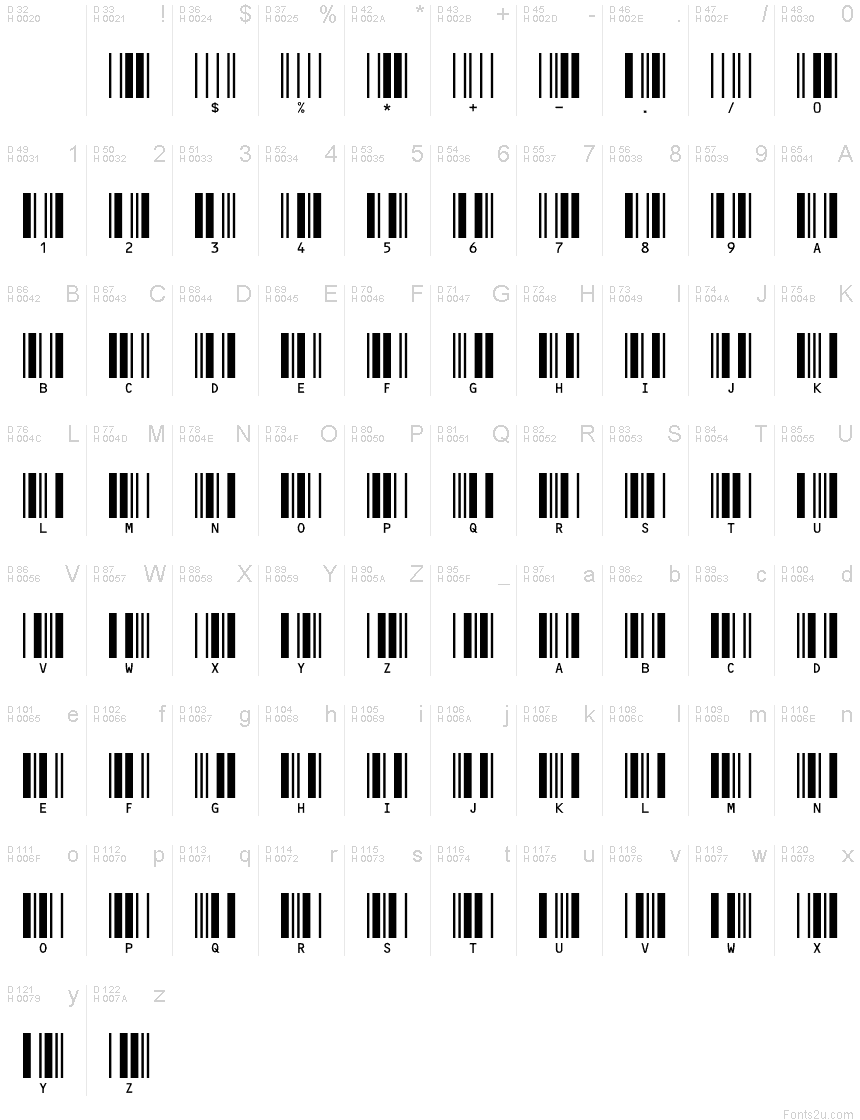
C39HrP24DlTt 字体
C39Hr 字体家族,包含 4 款字体
C39HrP24DlTt
由 Bear Rock Technologies Corp. 开发的 C39HrP24DlTt 是一款免费的条形码 dingbats 字体,无需任何额外工具或插件,即可将普通文本转换为清晰、可扫描的 Code 39 条形码。其垂直笔画精准且粗细均匀,充足的留白确保了每个条形码即便在小尺寸打印或打印在带有纹理的纸张上时,依然清晰易读。作为 C39Hr 字族的一员,它提供了可预测的间距,让生产团队在制作标签、挂牌和屏幕样机时倍感信赖。
使用 C39HrP24DlTt,您可以直接将这些可扫描的代码应用于包装概念设计、仓储标签、库存仪表板、票据、手册及科技感图形中。当您需要既实用又能在客户演示或成品文件中保持锐利视觉效果的条形码时,这款免费字体是您的理想之选。为了保持清晰的信息层级,建议将其与周围的正文文本搭配简单的无衬线体(Grotesk),并将条形码的尺寸设为比正文大一到两个级别。